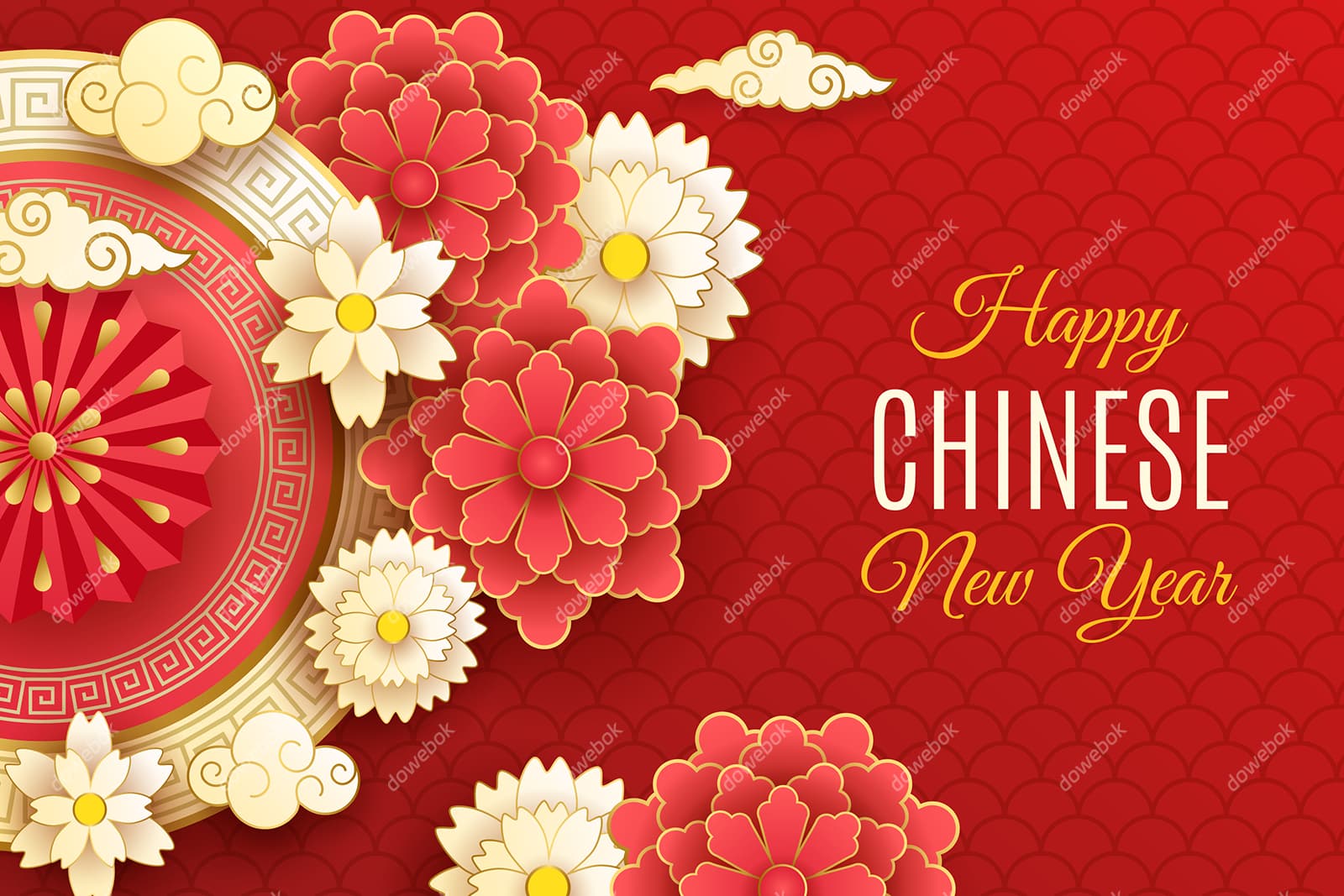
这是一款由花朵和祥云设计的春节快乐矢量素材,正红底衬鱼鳞纹理,左侧以红金团扇、回纹装饰搭配红白花饰与祥云,右侧 “Happy CHINESE New Year” 字样以鎏金字体呈现。红金主色调契合新年喜庆氛围,团扇、祥云等元素传递中式传统韵味,剪纸质感添立体美感,风格热烈雅致,适配新年贺卡、装饰物料等场景。